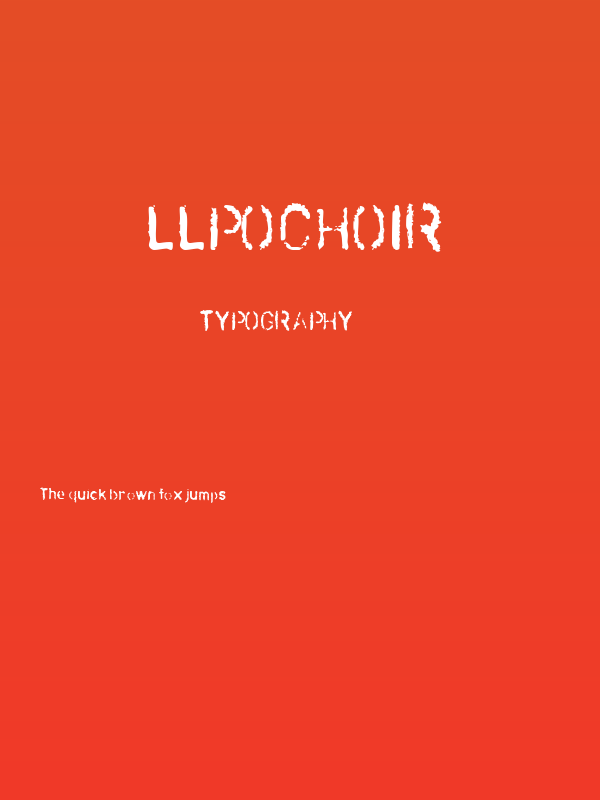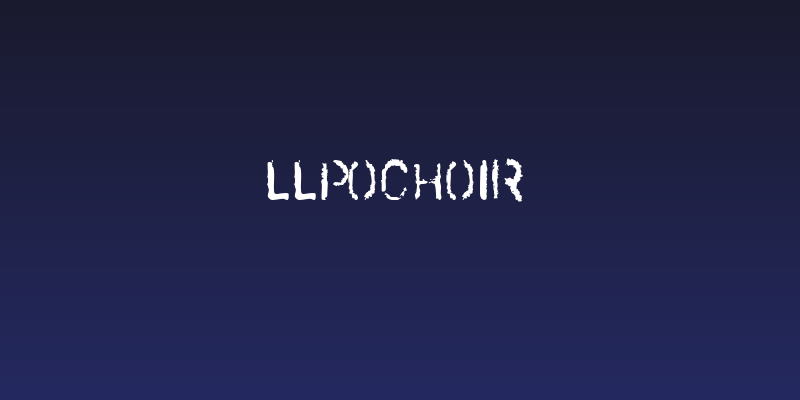
LLPochoir Font
✎ Stencil
| Stile generale | Industrial, Rugged |
| Progetti proposti | Ideal for poster designs, album covers, urban-themed branding, and any project requiring a bold, industrial look. |